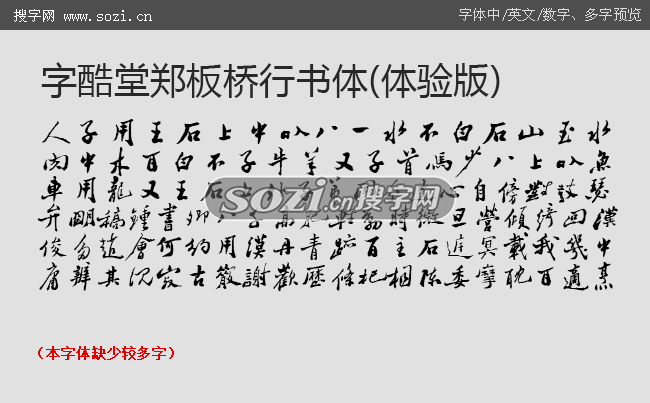
字酷堂鄭板橋行書(shū)體(體驗(yàn)版)
搜字網(wǎng)提供一款字酷堂鄭板橋行書(shū)體(體驗(yàn)版)手寫(xiě)中文書(shū)法字體下載,字酷堂鄭板橋行書(shū)體是一款非常漂亮的手寫(xiě)字體,高度還原了鄭板橋的行書(shū)字體,字體極具藝術(shù)風(fēng)格,每筆每畫(huà)都給人一種飄逸灑脫的感覺(jué),而在飄逸之余不失大氣,能夠應(yīng)用于平面設(shè)計(jì)、名片設(shè)計(jì)、廣告創(chuàng)意、印刷等場(chǎng)合應(yīng)用。